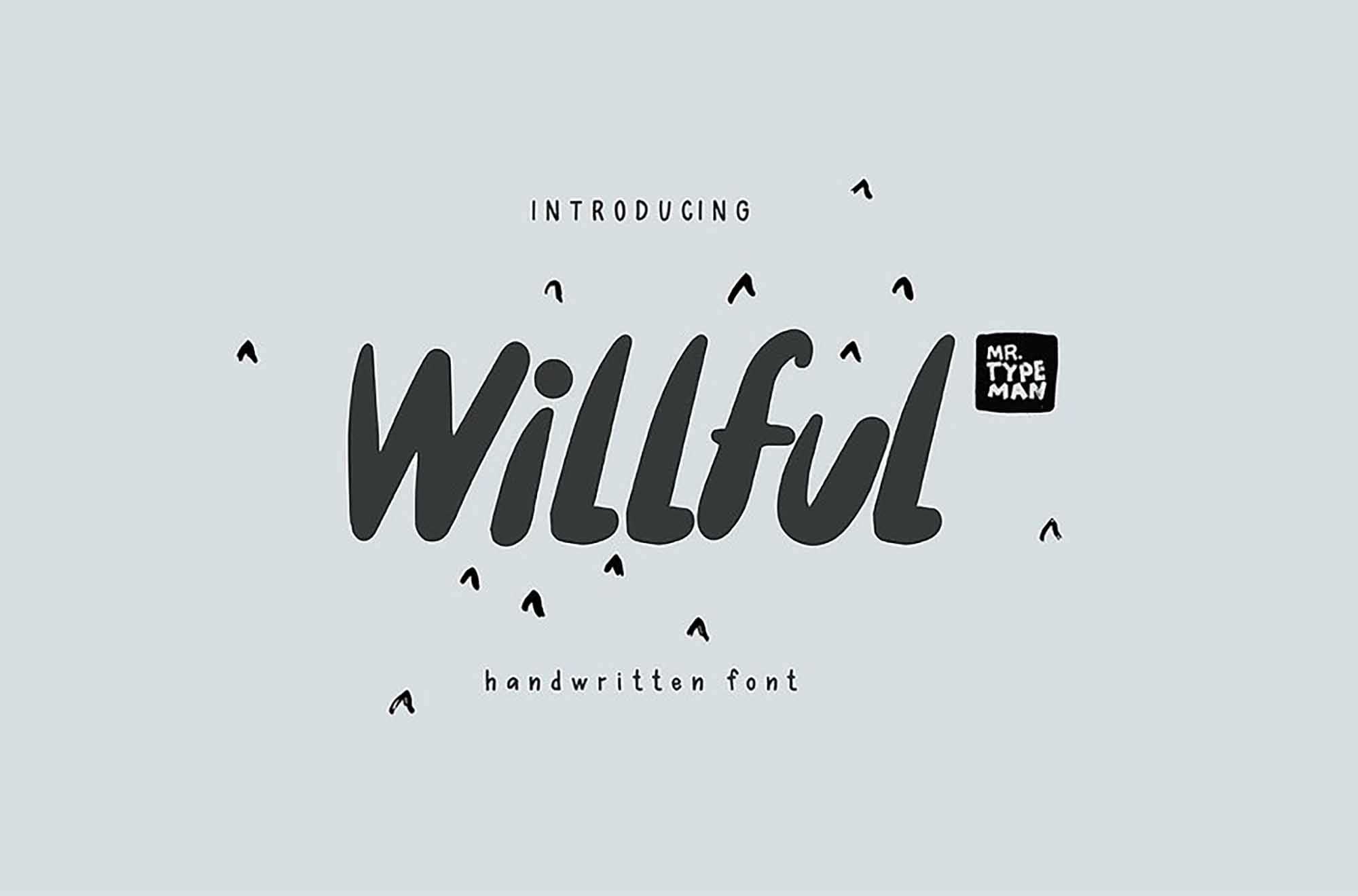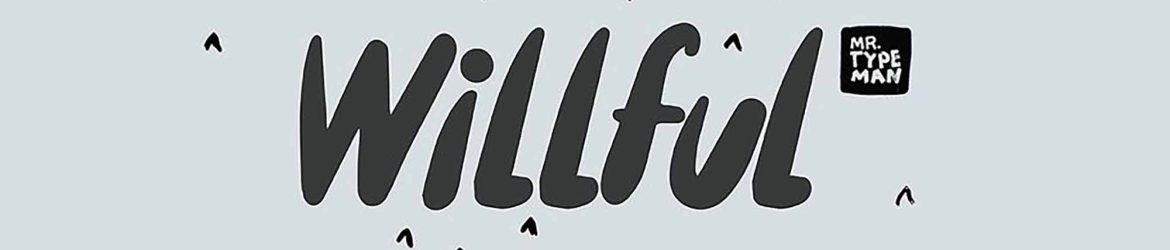
A Willful Handwritten Font é uma fonte de desenho manual, criada para levar o texto para um nível mais expressivo e criativo. Este recurso gráfico é perfeito para quem busca dar um toque especial a qualquer projeto de design. Quando você usa a Willful Handwritten Font, é como se estivesse invocando a habilidade artística natural daqueles que têm a atitude corajosa de expressar-se da maneira que consideram correta. Ela reflete a ideia de que cada passo em direção à realização artística deve ser feito de uma maneira que possa impactar positivamente os espectadores. É como se cada passo fosse uma chance de mudar a perspectiva de quem está olhando para o seu trabalho, e agora é seu próximo passo, uma passada bem intencionada e determinada. Envolvente e natural, essa fonte traz um toque único e vibrante a qualquer design.